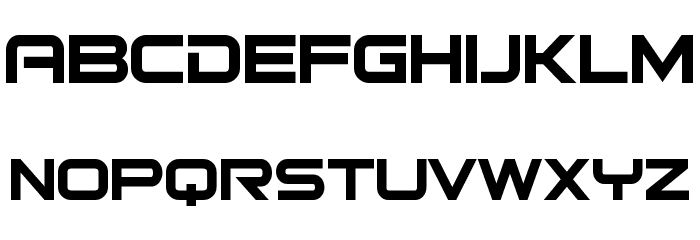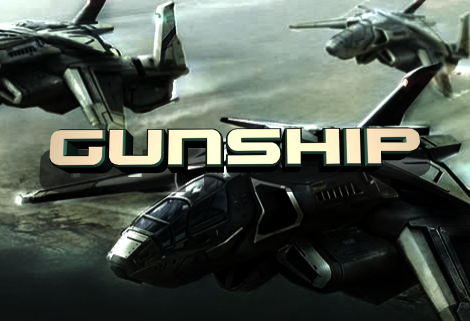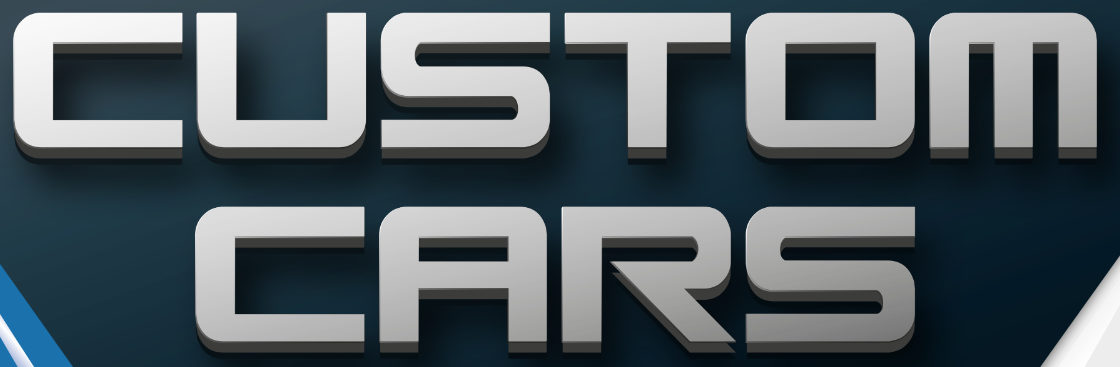
Technoide Schrift gesucht
Hatten wir die nicht neulich erst?
Ich glaube, du meintest das hier. Ist aber nur entfernt ähnlich ;-) Aber Ray Larabie ist prinzipiell keine schlechte Idee bei solchen Schriften (ebenso wie Jeff Levine).
ich habe da als nächstest die "Gunship" von Iconian Fonts anzubieten. Bitte Groß-Klein-Schreibung beachten! Das R ist ein kleines ...
Ist das nahe genug dran? Irgendwie passt die Strichdicke nicht so ganz?